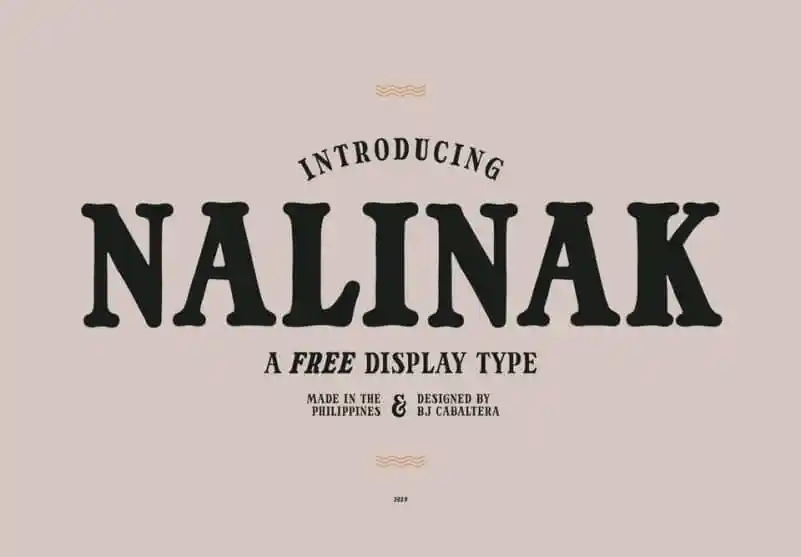
A Nalinak Serif Font é uma fonte serif que traz à tona a elegância dos estilos antigos de letras manuscritas com um toque moderno de distorção suave e contraste suave entre os traços. Desenvolvida por Bj Cabaltera na plataforma 99designs, essa fonte oferece uma aparição fresca e não monótona para textos semânticos e gráficos. Inspirada nos detalhes cuidadosamente elaborados dos antigos artistas de letras manuscritas, a Nalinak Serif é projetada para criar um ar elegante e sofisticado em seus espaços de texto. Com quatro estilos disponíveis – regular, itálico, bold e bold italic – esta fonte se adapta facilmente a várias aplicações. Ela inclui alfabeto maiúsculo básico, números e pontuação essencial, além de um conjunto adicional de caracteres para aqueles que precisam de mais liberdade criativa. A Nalinak Serif é uma opção ideal para designers gráficos, produtores de conteúdo digital e qualquer pessoa interessada em incorporar um toque vintage e sofisticado em seu trabalho. Suas formas afiadas, contrastes suaves e estilo antigo combinam perfeitamente com os estilos mais modernos, criando texturas ricas e personalizadas.